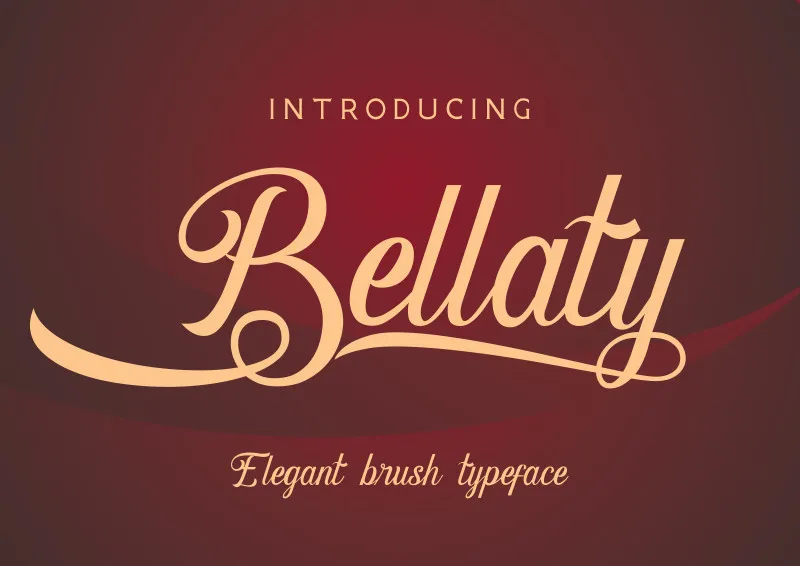
Bellaty Brush Scripts Font – Download Grátis
A Bellaty Brush Scripts Font é uma criação do designer SheillaType, trazendo um estilo único de traços de pincel e letras script, com linhas limpas e swashes únicos que dão ao texto uma aparência intrigante. Este tipo pode ser usado tanto para logotipos quanto para desenhos de cartas, textos em destaque, headlines e diversas outras aplicações de design. Esta font é perfeita para quem busca algo único e dinâmico no seu trabalho gráfico. Descarregue-a agora e aproveite a sua capacidade única nesta coleção de tipos Brush Fonts do designer tepikalistudio.